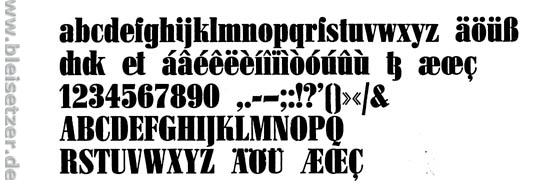
Antiqua Ultra oder doch was anderes?
ich suche diese Schrift
vom Text "Hunderttausend Deutsche Mark"
ich dachte, dass die Antiqua Ultra ihr sehr ähnlich ist und hätte die Frage, ob es die auch kostenlos in einer abgewandelten Version erhältlich ist.
welche schrift meinst du mit antiqua ultra? die hier?
die ?nde ich nicht wirklich ähnlich zu deiner vorlage. vielleicht eher so was:
auch keine 1:1-entsprechung, die sich vermutlich nicht auftreiben lässt, aber näher dran.
Das ist mit hoher Wahrscheinlichkeit die Pergamon. Jedenfalls stimmt der sonstige Text überein. Ich nehme also an, daß für »Hunderttausend Deutsche Mark« keine völlig andere Schrift, sondern die schmalfette Pergamon verwendet wurde. Aber ausgerechnet von der schmalfetten habe ich kein Muster, um das zu verifizieren.
Hier findet sich ein Beispiel:
Scheint zu stimmen, zumindest stimmt das sehr charakteristische k.
Allerdings scheint die Schrift auf der Aktie doch etwas breiter zu laufen, oder täuscht das? Vielleicht ist es doch keine schmalfette, sondern eine extrafette; die Pergaon läuft an sich ja schon nicht sehr breit.
Bei bleisetzer findet sich noch die schmalhalbfette:
Ich würde mal sagen, das ist sie. Aber warum sieht die jetzt so viel mächtiger aus als die schmalhalbfette auf Deinem Muster? Hat der gute Georg da eine Pergamon im Kasten gehabt, und weil die irgendwie schmal und halbfett aussieht, diese als »schmalhalbfett« benannt, obwohl die ab Gießerei vielleicht doch schmalfett oder weiß der Geier wie geheißen hat? Oder er hat irgendwoher schon falsch beschriftete Kästen übernommen? Schade, daß er nicht mehr unter uns weilt, sonst könnten wir das vielleicht klären.
Das weiß ich leider nicht, ich habe nur danach gesucht und eben das erste Beispiel bei typografie.info und das zweite bei bleisetzer gefunden.
Bei klingspor findet sich noch jenes Beispiel:
Das bringt nicht wirklich Klarheit, ich vermute aber dass da die Angaben des Herrn Bleisetzer nicht ganz korrekt sind.